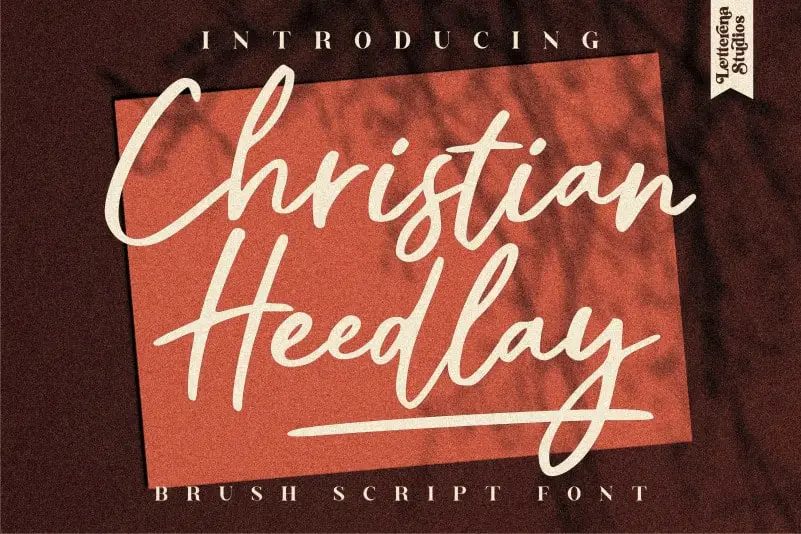
Christian Heedlay Handwritten Font – Fonte Grátis
Christian Heedlay Handwritten Font
Christian Heedlay Handwritten Font é uma elegante tipografia com traços a mão livre inspirada na calligrafia clássica, mas com um toque contemporâneo e moderno. Desenvolvida para os designers que valorizam o equilíbrio entre beleza e simplicidade, essa fonte atende aos mais exigentes projetos gráficos. Não é fina nem grossa demais, mantendo sempre um padrão de qualidade altamente aceitável. Inspirada na perfeição da calligrafia clássica, esta tipografia foi criada para destacar e valorizar a beleza em seus trabalhos, tornando seu design mais atraente e sofisticado. Não é apenas uma fonte a mão livre, mas uma ferramenta de design versátil que enriquece qualquer projeto gráfico com sua autenticidade e elegância.